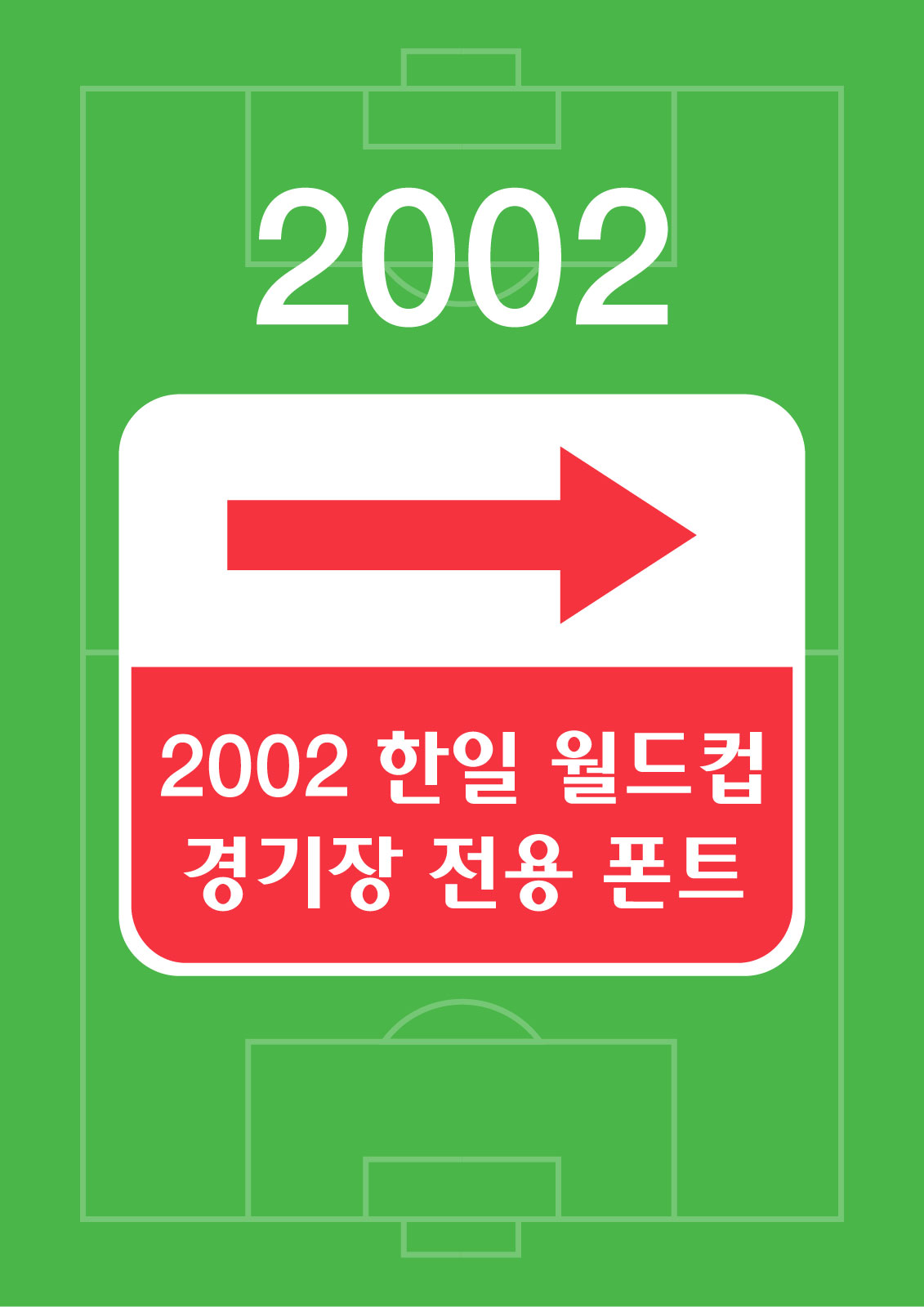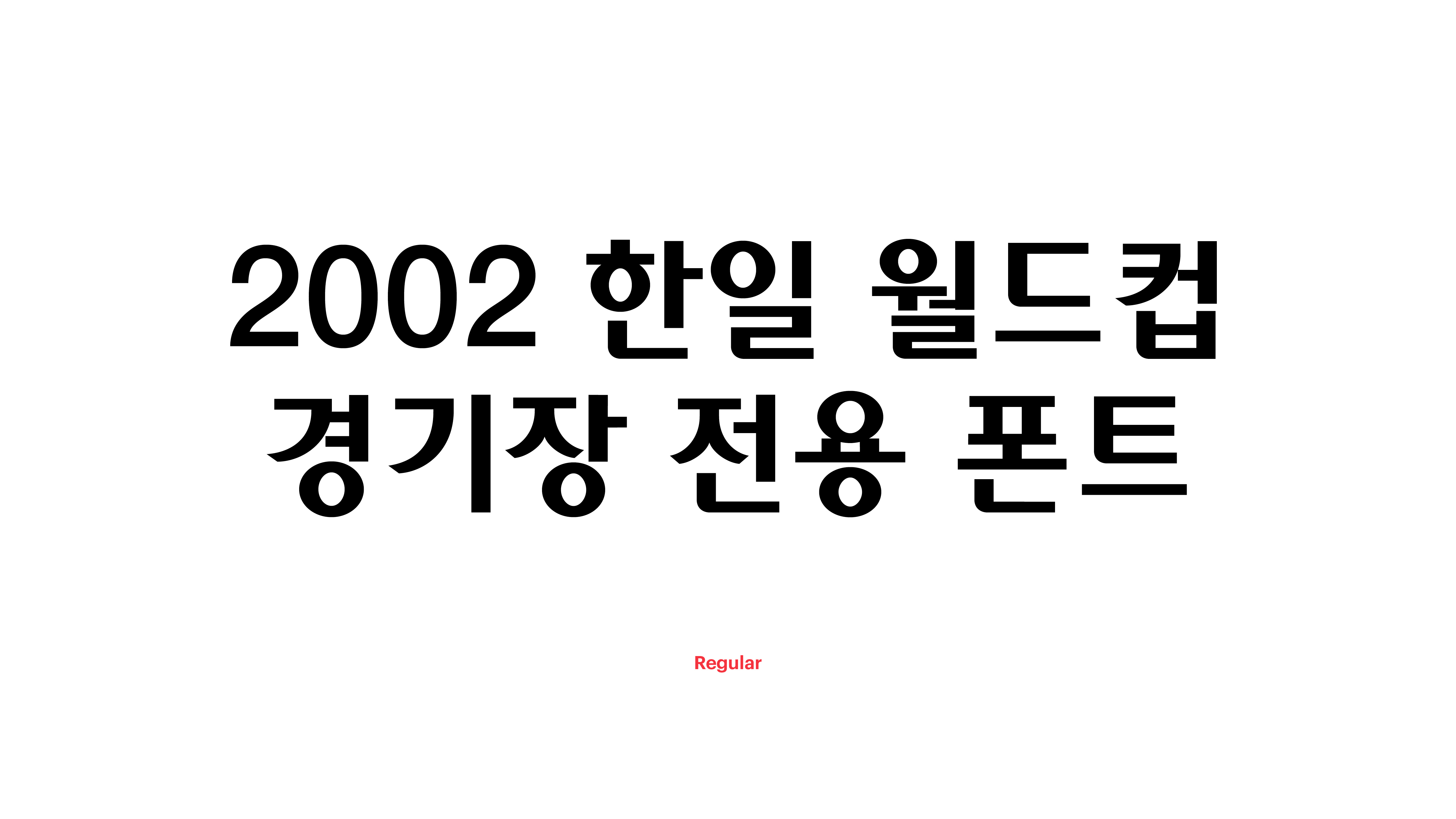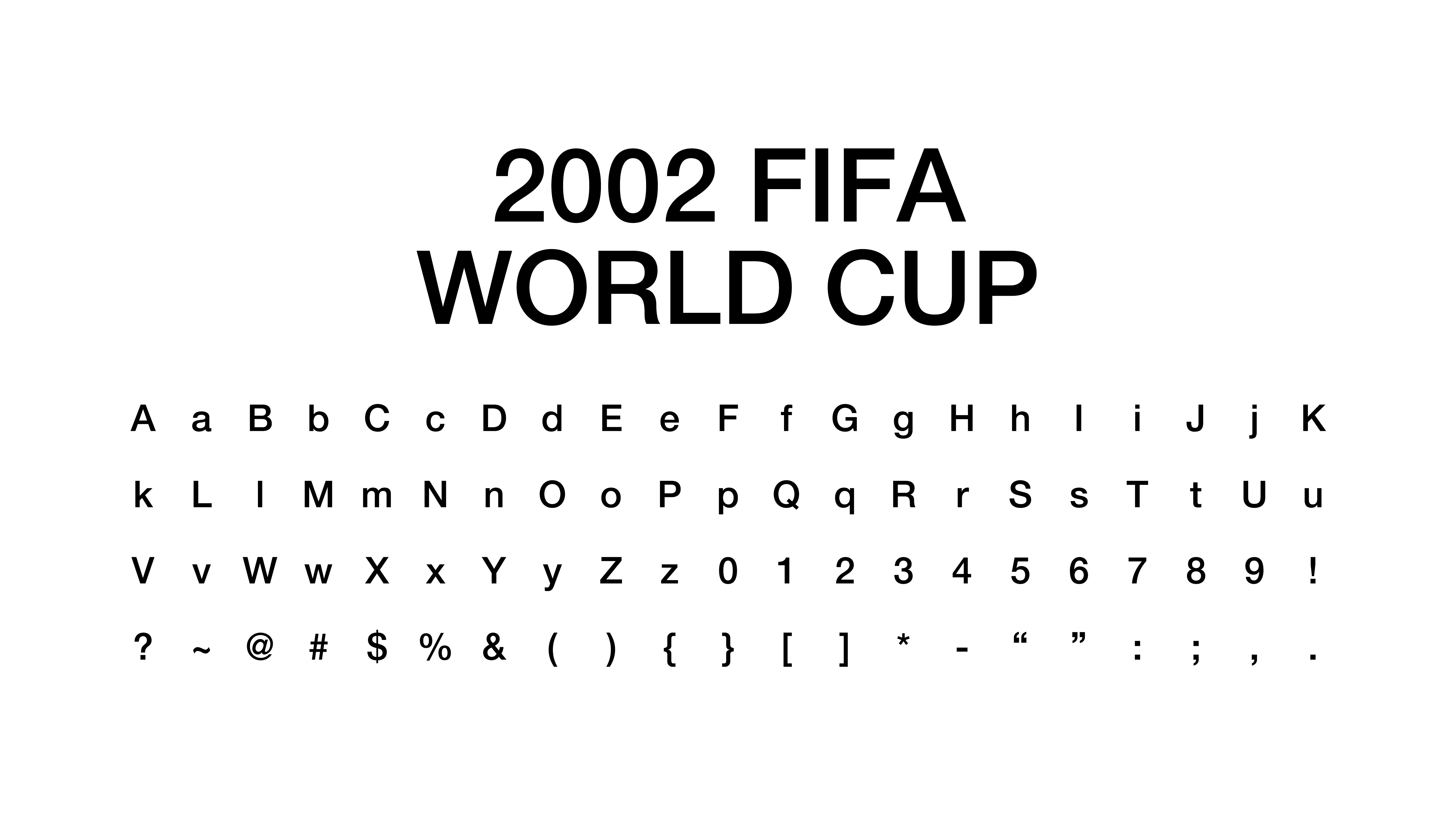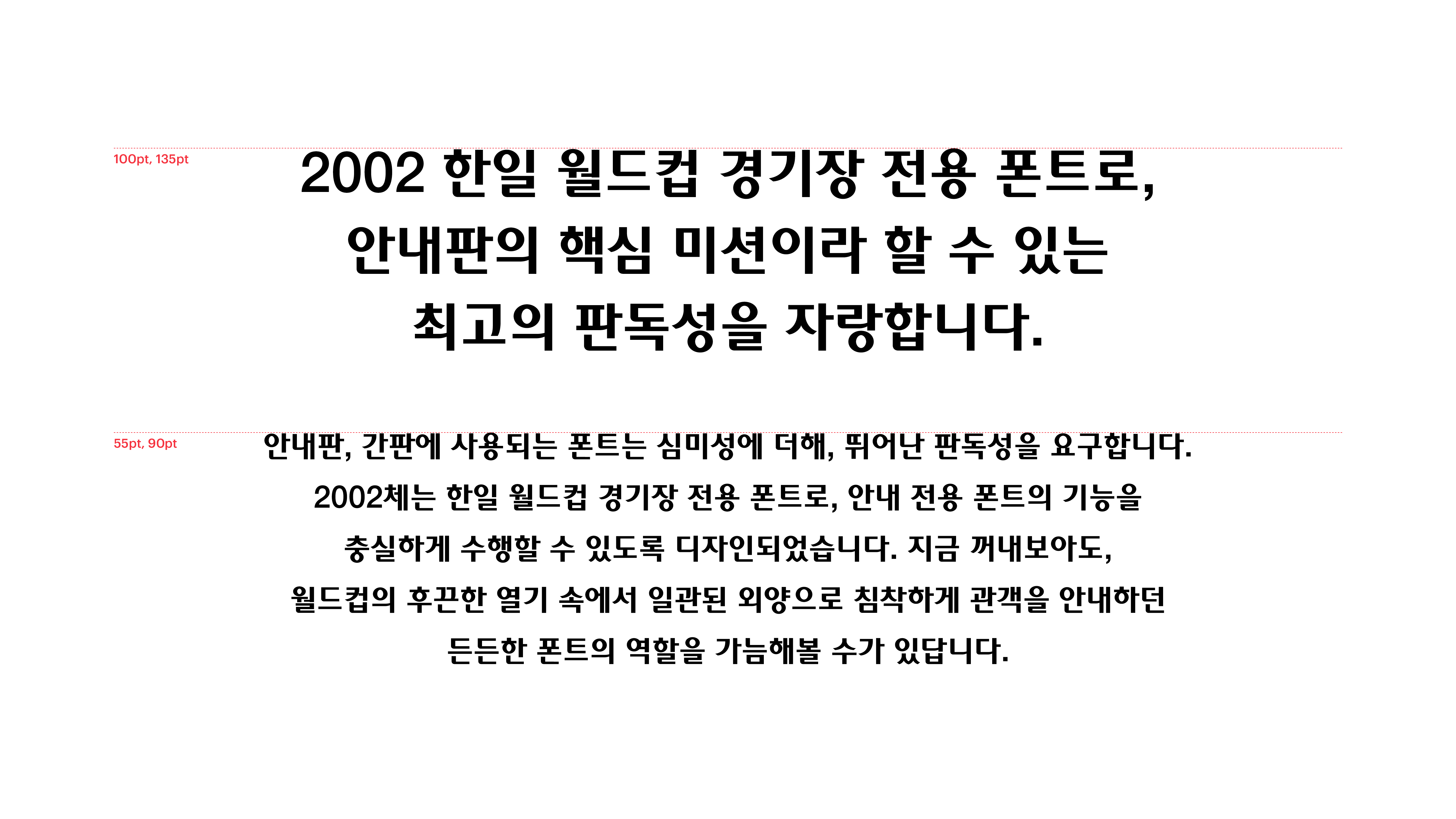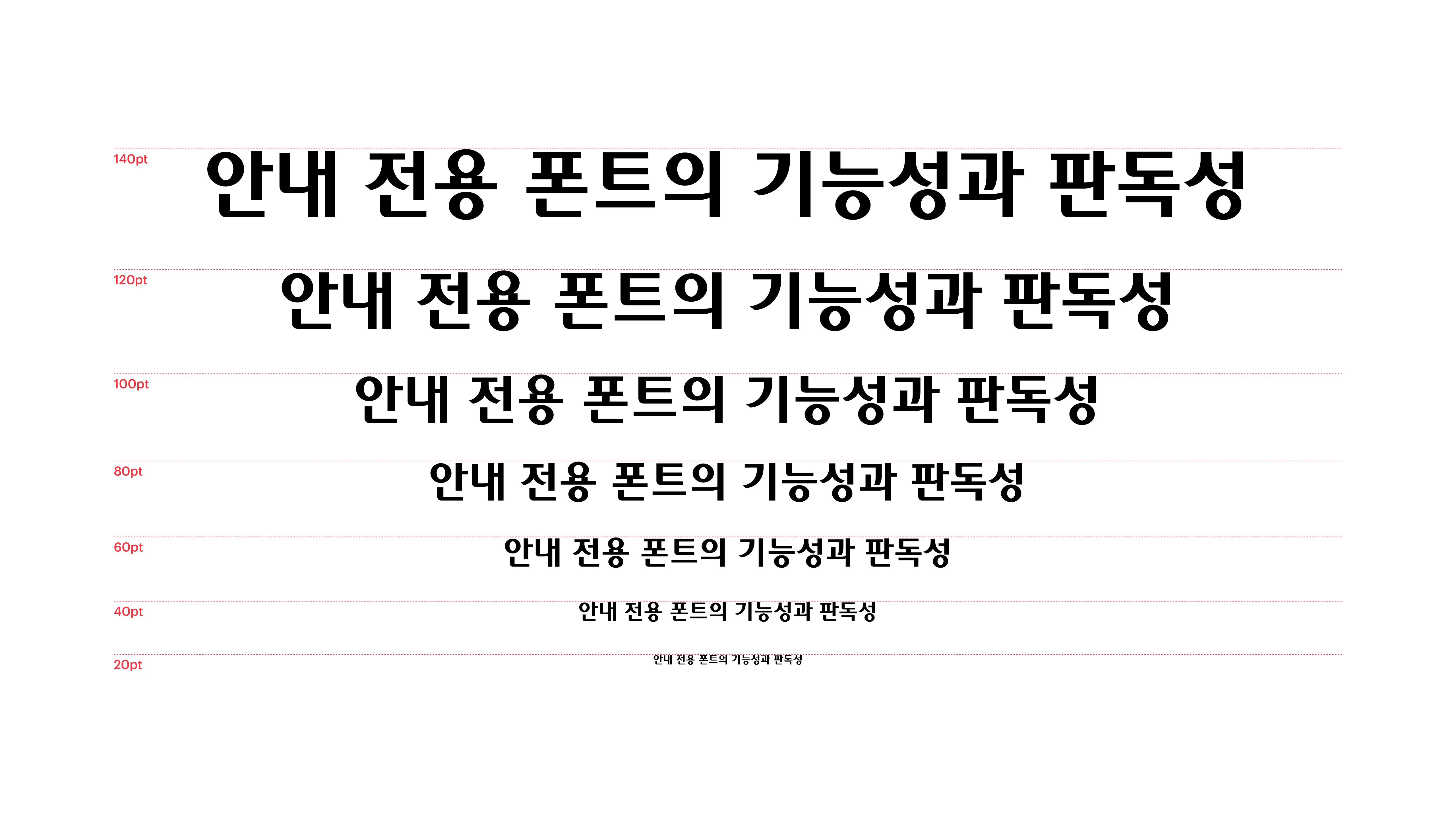
2002
Yoon 2002
안내판, 간판에 사용되는 폰트는 심미성에 더해, 뛰어난 판독성을 요구합니다. 2002체는 한일월드컵 경기장 전용 폰트로, 안내 전용 폰트의 기능성을 한눈에 살펴볼 수 있도록 디자인되었습니다. 지금 꺼내보아도, 월드컵의 후끈한 열기 속에서 일관된 외양으로 침착하게 관객을 안내하던 든든한 폰트의 역할을 가늠해볼 수가 있답니다.